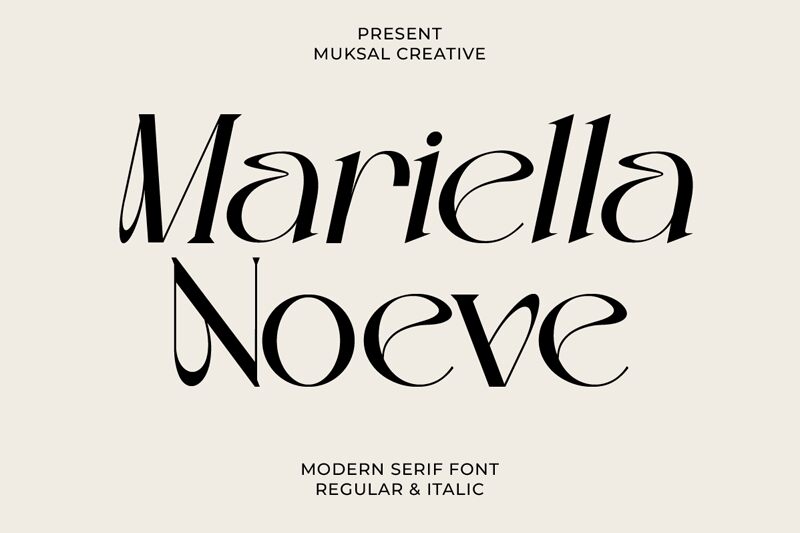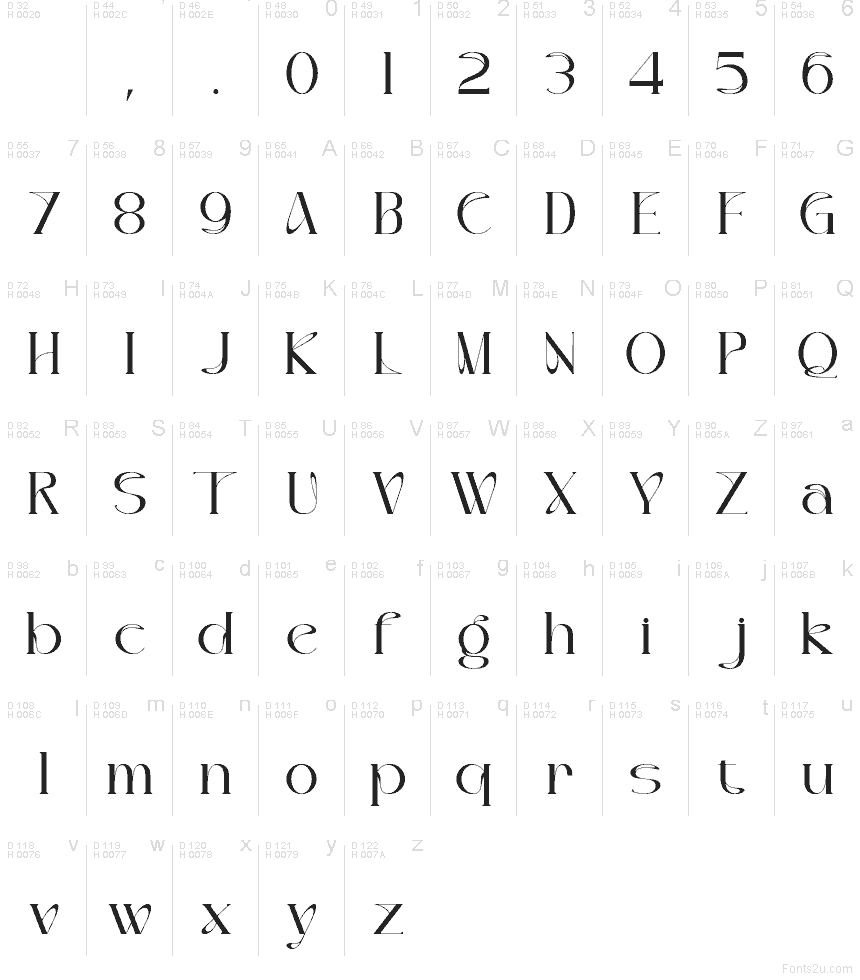
Mariella Noeve Regular
Mariella Noeve je bezplatné retro display písmo od Muksal Creative, které využívá vysokou siluetu s vysokým kontrastem a dlouhými jemnými křivkami, jež přesahují hlavní tahy písmen. Toto opakující se střídání úzkých vertikál a širokých oválných tvarů dodává písmu vytříbený, plakátový rytmus, který je mnohem výraznější než u běžného patkového písma.
Skvěle se hodí pro módní branding, butikové obaly, nadpisy v časopisech, etikety kosmetiky nebo názvy na pozvánkách, kde tyto protažené křivky samy o sobě vytvářejí osobitý styl. Krátké nadpisy obzvláště těží z lehkého švihu tohoto fontu, který vytváří elegantní obrys bez potřeby dalších zdobných prvků kolem textu.